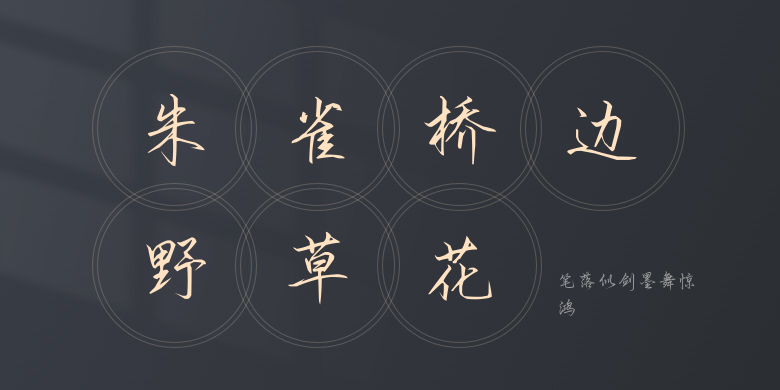
笔落似剑墨舞惊鸿
笔落似剑墨舞惊鸿,这款字体结构工整、笔画清晰,兼顾美观与易读性,适用于标题、正文、海报、包装、LOGO 等多种场景。字形优雅稳定,风格百搭耐看,适配日常排版与创意设计,让文字呈现更舒适、更具质感。笔落似剑墨舞惊鸿一笔一画,皆是细节,以均衡的比例、流畅的线条打造舒适视觉体验,字形端正大气,风格简约现代。无论是商业设计、品牌宣传还是日常排版,都能轻松驾驭,让文字更有格调与力量。笔落似剑墨舞惊鸿字体下载。